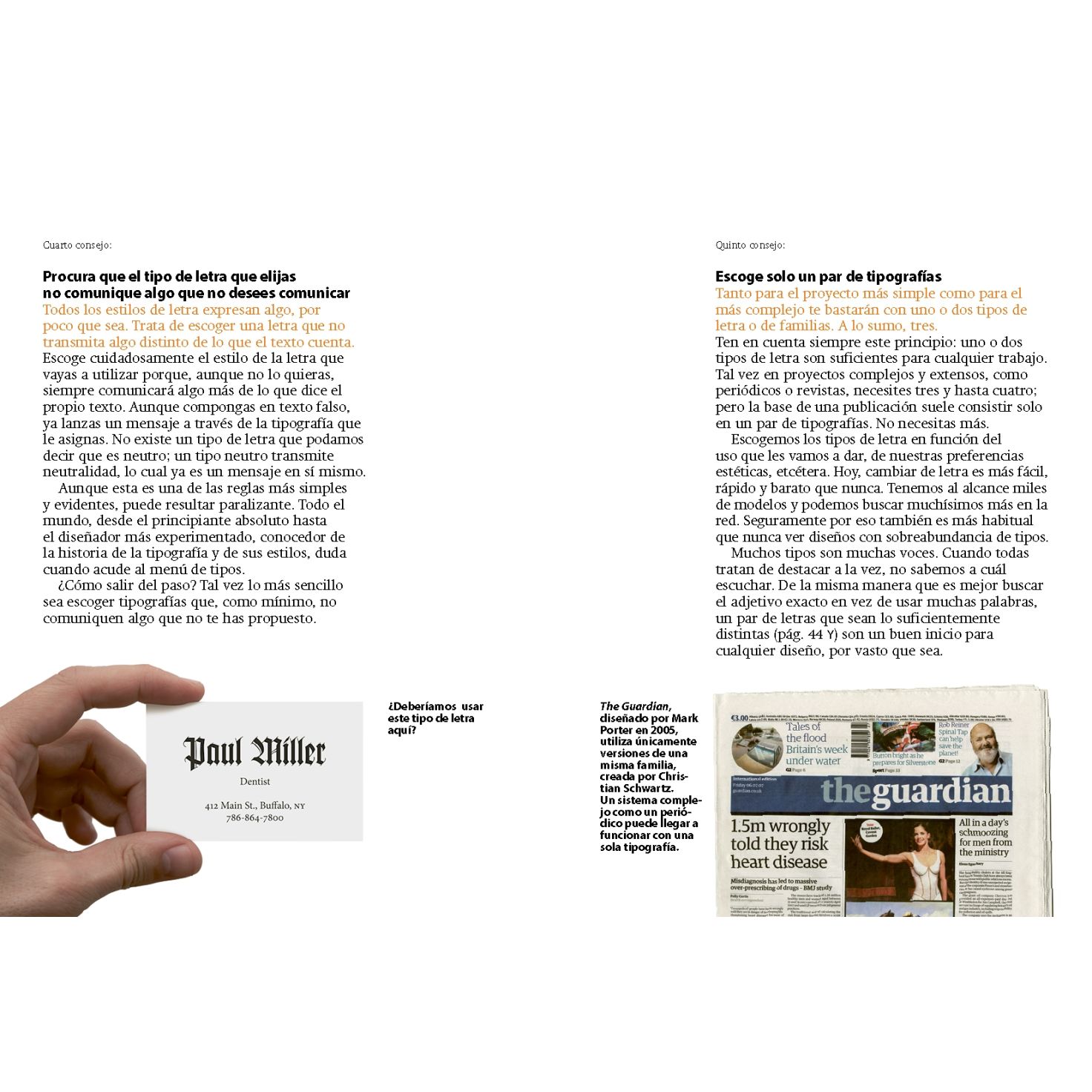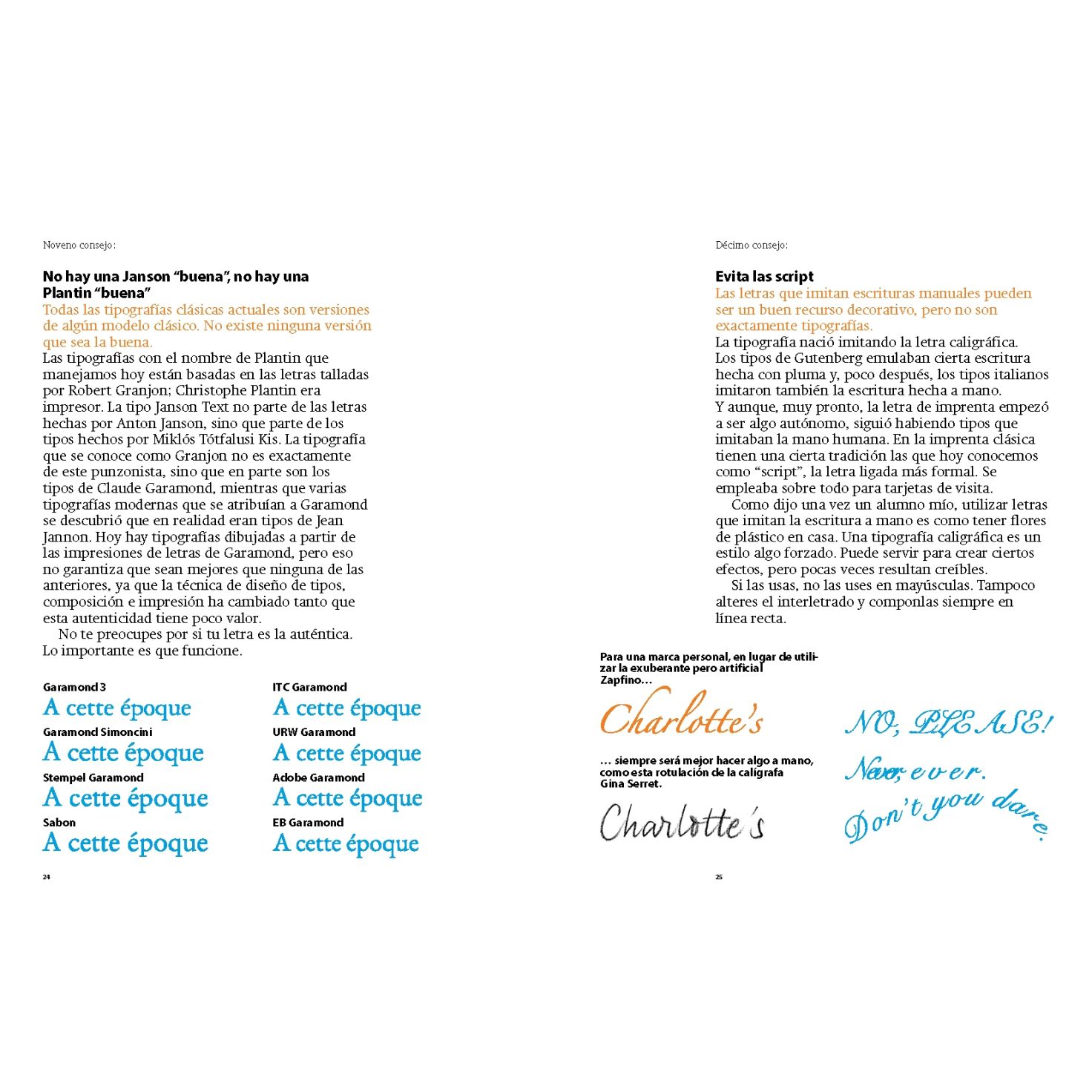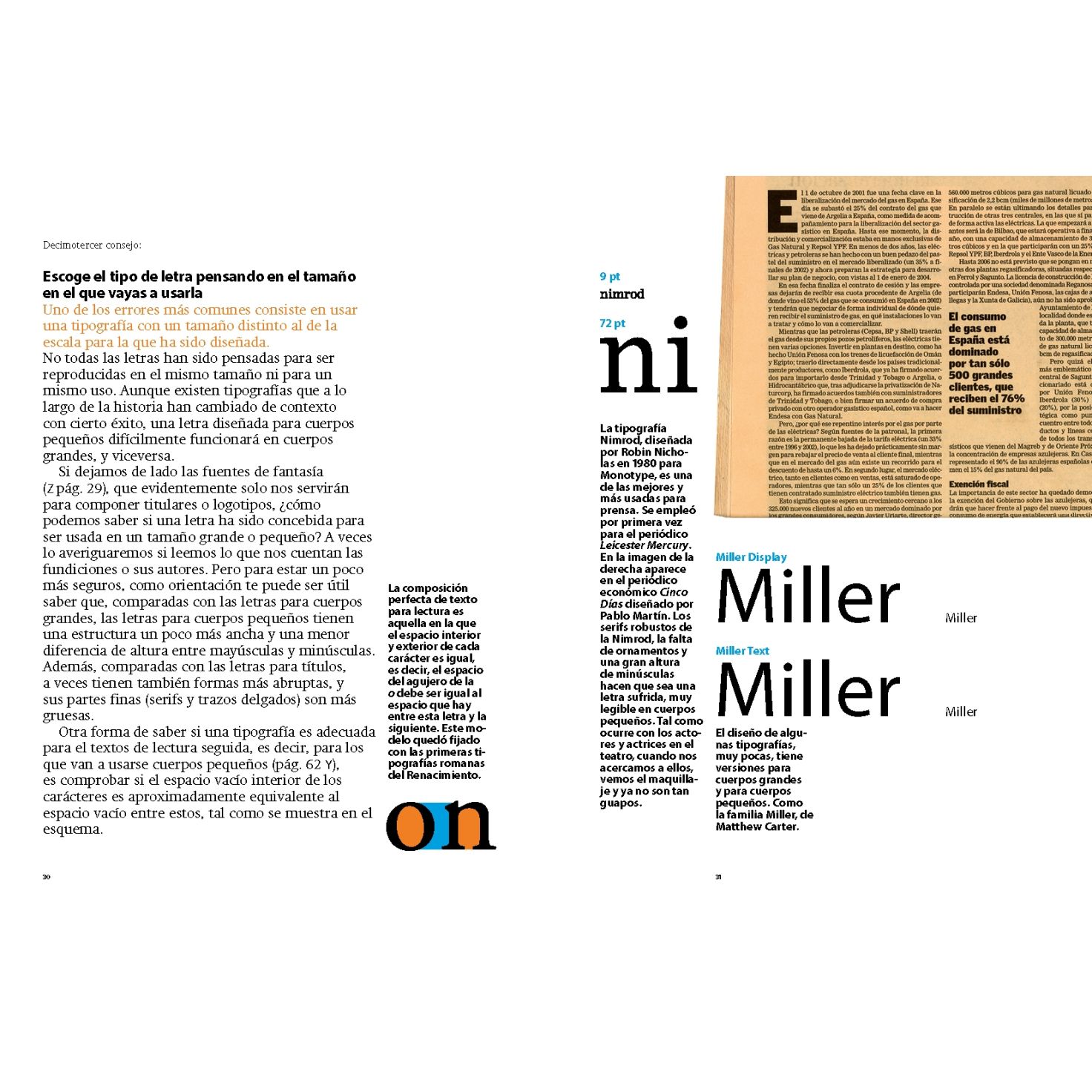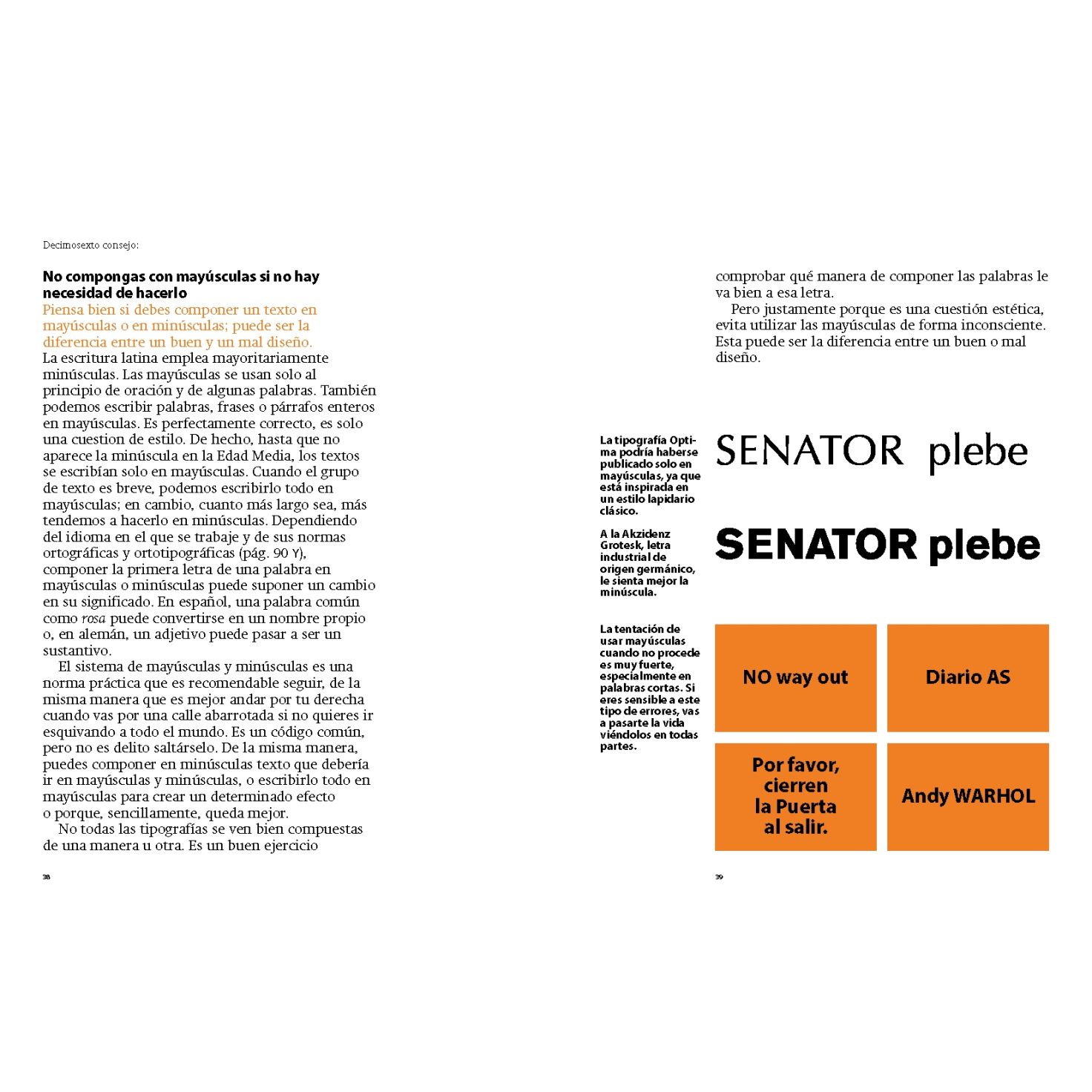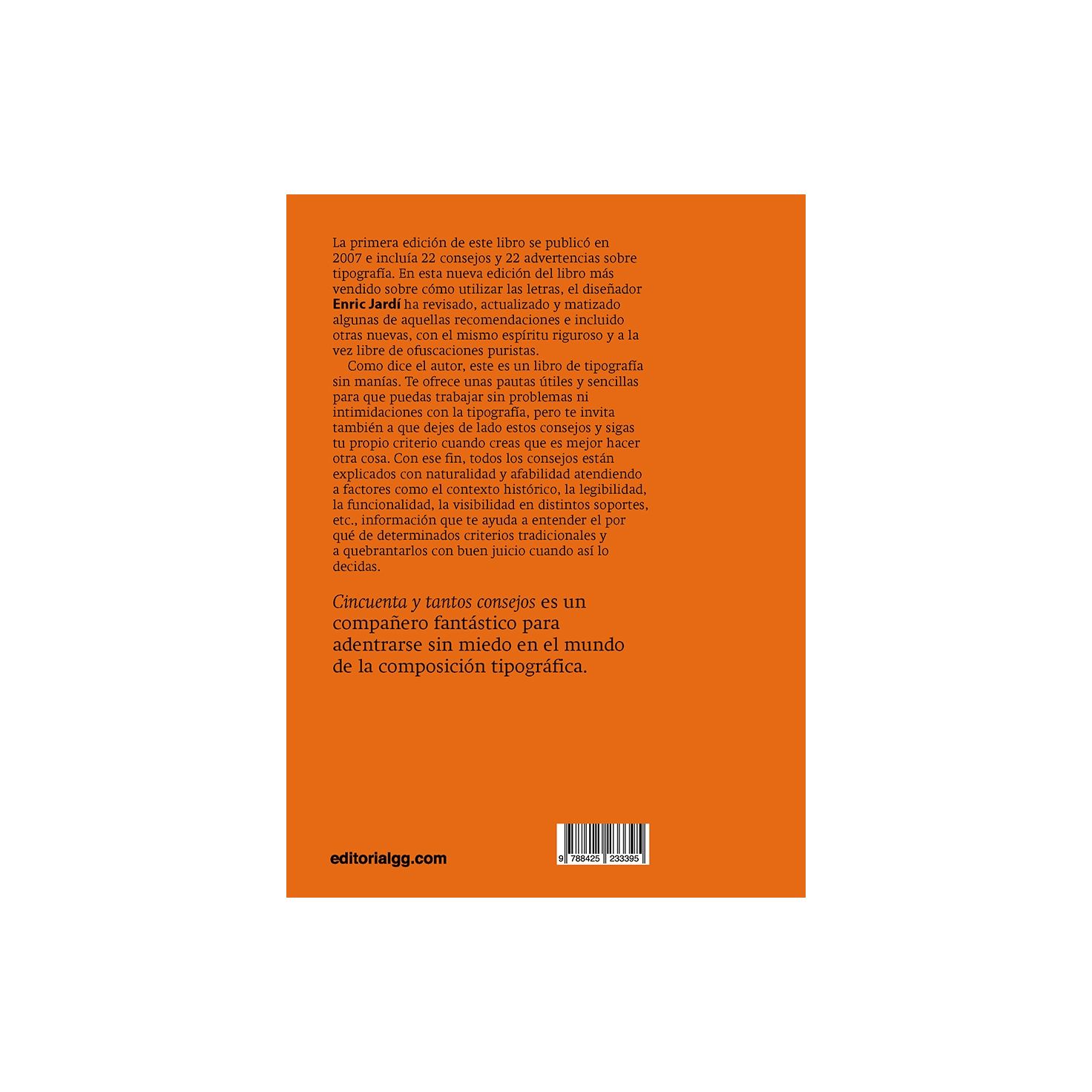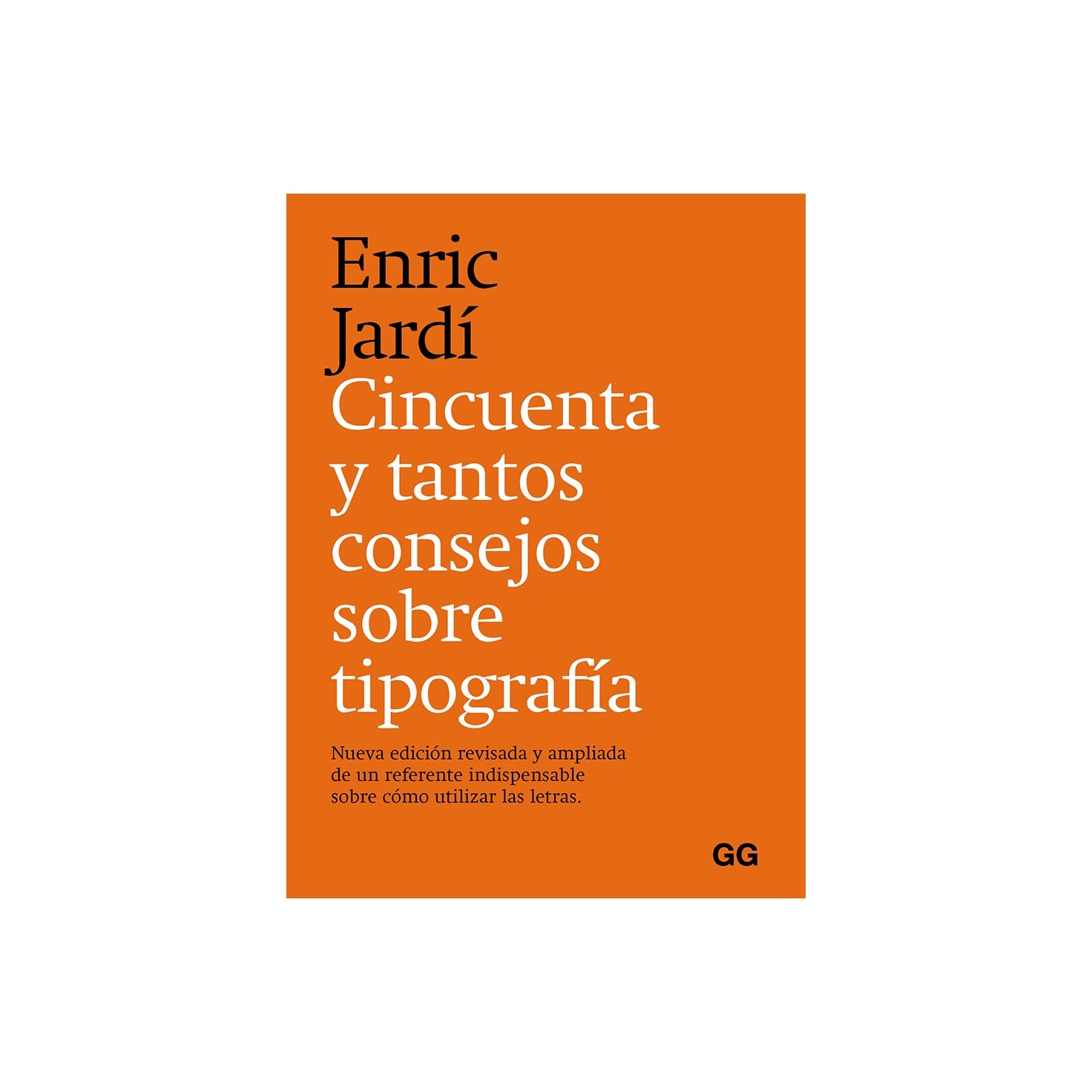
Cincuenta y tantos consejos sobre tipografía
Nueva edición revisada y ampliada de un referente indispensable sobre cómo utilizar las letras.
La primera edición de este libro se publicó en 2007 e incluía 22 consejos y 22 advertencias sobre tipografía. En esta nueva edición del libro más vendido sobre cómo utilizar las letras, el diseñador Enric Jardí ha revisado, actualizado y matizado algunas de aquellas recomendaciones e incluido otras nuevas, con el mismo espíritu riguroso y a la vez libre de ofuscaciones puristas.
Como dice el autor, este es un libro de tipografía sin manías. Te ofrece unas pautas útiles y sencillas para que puedas trabajar sin problemas ni intimidaciones con la tipografía, pero te invita también a que dejes de lado estos consejos y sigas tu propio criterio cuando creas que es mejor hacer otra cosa. Con ese fin, todos los consejos están explicados con naturalidad y afabilidad atendiendo a factores como el contexto histórico, la legibilidad, la funcionalidad, la visibilidad en distintos soportes, etc., información que te ayuda a entender el por qué de determinados criterios tradicionales y a quebrantarlos con buen juicio cuando así lo decidas.
Cincuenta y tantos consejos es un compañero fantástico para adentrarse sin miedo en el mundo de la composición tipográfica.
Introducción
No hace falta que te aprendas cómo se llaman todas las partes de la letra
Todas las tipografías se leen bien
Clasifica las tipografías como mejor te parezc
Procura que el tipo de letra que elijas no comunique algo que no desees comunicar
Escoge solo un par de tipografías
No te equivoques de medio
No utilices sucedáneos
No recrees estilos históricos
No hay una Janson “buena”, no hay una Plantin “buena”
Evita las script
Rechaza los tipos con caracteres caprichosos
No escojas letras temáticas
Escoge el tipo de letra pensando en el tamaño en el que vayas a usarla
Usa tipos que estén diseñados para tu idioma
Retoca las palabras sueltas
No compongas con mayúsculas si no hay necesidad de hacerlo
Si resulta imperceptible, puedes condensar y expandir las letras
No intentes convertir la letra en una imagen: la letra ya es una imagen
Asegúrate de que tu tipo llega hasta el final
No inclines letras hacia la izquierda ni compongas en vertical letras horizontales
No pongas juntas dos letras que se parezcan demasiado
No compongas juntos pesos con distintos grados de condensación
Iguala los tamaños de letra cuando combines dos tipos distintos
Puedes dejar espacio extra entre mayúsculas
No añadas espacio extra entre minúsculas
No crees demasiadas categorías
No toques demasiado los valores por defecto
Si te dejan, compón a caja izquierda
Invita a la lectura
¿Seguro que te hace falta una retícula?
Olvida el cícero, las picas y los puntos
Haz márgenes regulares
No hagas líneas demasiado largas ni demasiado cortas
No te afanes con el número de página
Marca los párrafos convenientemente
No combines columnas centradas con otras no centradas
Iguala el número de líneas de las columnas
No dejes palabras sueltas
No construyas sistemas de organización del texto que no sean intuitivos
Cuadra las líneas de texto
Cierra el interlineado y el interletraje en los cuerpos grandes
Si compones en mayúsculas, cierra la interlínea
Aumenta la interlínea cuando construyas párrafos en negativo
Olvídate del kerning
Elige cuidadosamente los caracteres
Cuida los números
Evita según que ligaduras
No utilices falsas negritas, falsas cursivas ni falsas versalitas
Las negritas son para destacar palabras
Evita las negritas de las romanas
Papel y pantalla se ven distintos
Escoge buenos tipos para pantalla y aplícales el valor de cuerpo adecuado